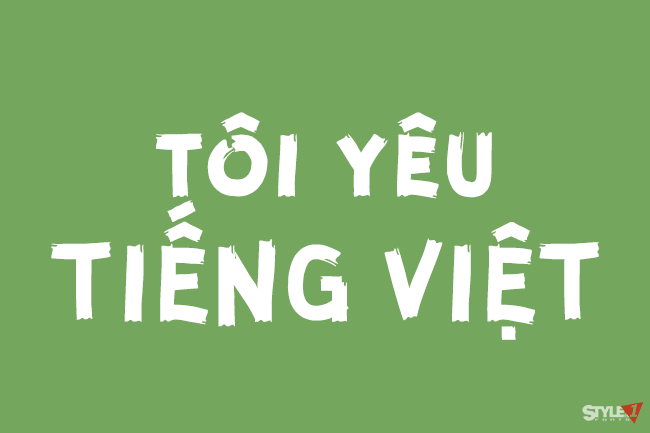
Guerrilla là một font miễn phí mang nét thô ráp, pha chút graffiti và hương vị brush, được thiết kế bởi Carlos Zubia đến từ Chihuahua, Mexico.
Nhà thiết kế: Zubia
Nhà phát hành: Fontfabric